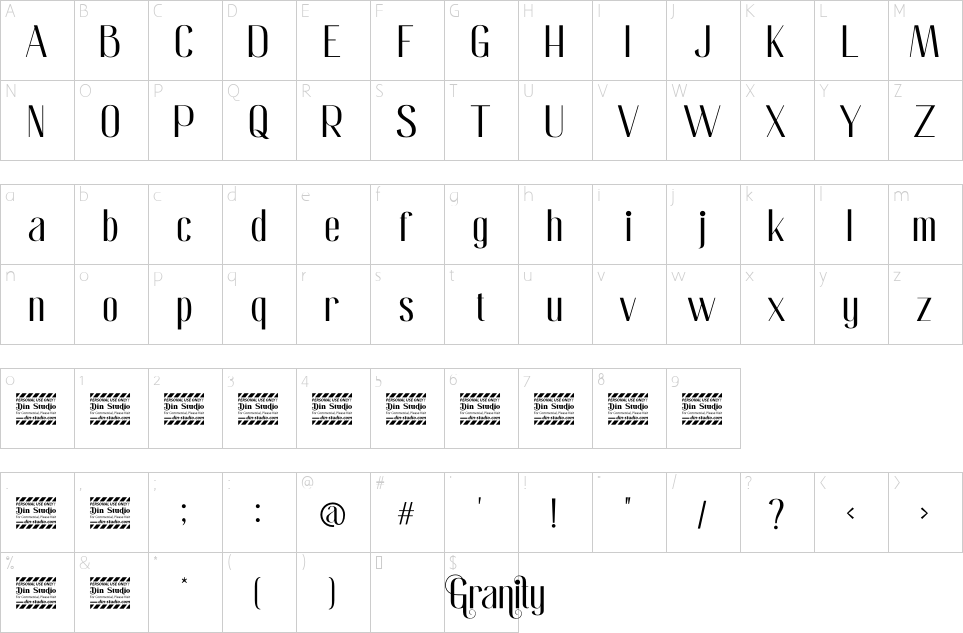
Granity Font
A Granity Font é uma opção divertida para quem está procurando por uma fonte moderna e elegante para projetos pessoais ou profissionais. Desenvolvida pelo designer Natha Type, a Granity traz um toque de minimalismo e simplicidade que combina perfeitamente com diversos estilos de design. Esta fonte foi popular entre os fãs por sua facilidade de uso, especialmente em projetos digitais como emails ou websites. Com apenas 6,522 downloads, a Granity ainda é uma opção segura para quem deseja adicionar um toque único e moderno ao seu trabalho sem riscos de violação de direitos autorais. Descubra por si mesmo o encanto desta fonte e encontre seu estilo personalizado com a Granity Font.
Mapa de caracteres da fonte Granity Font